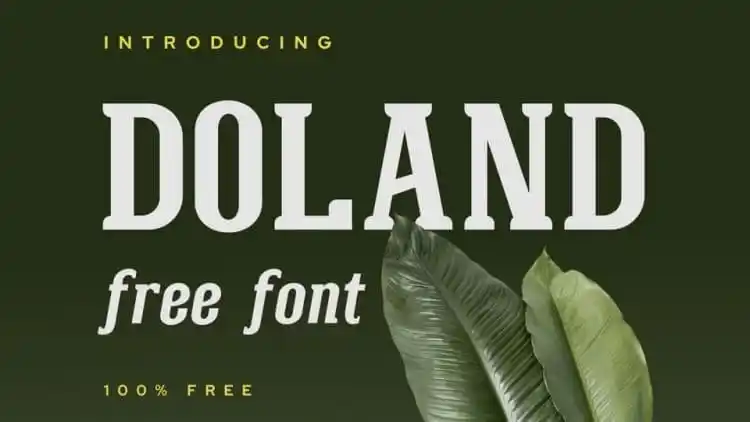
Doland Serif Font – Download Grátis
A Fonte Doland Serif é uma serif typeface vintage que foi criada com destaque para impacto visual. Typra Studio trouxe uma combinação única e moderna de aparência, ao mesmo tempo amigável e emocional forte à serifa dessa fonte. Com seus finos finais afiados, ela cria um apelo imediato em ambientes de exposição. Mas é no uso para textos que a Doland Serif se destaca ainda mais. Suas estruturas retangularmente arredondadas e delicadas são adaptadas naturalmente para blocos de texto, permitindo uma legibilidade excelente em qualquer tamanho e formato. Essa fonte oferece o melhor dos dois mundos: o charme das serif typefaces tradicionais com a modernidade de um design atual, fazendo-a perfeitamente adequada para ambientes digitais atuais.